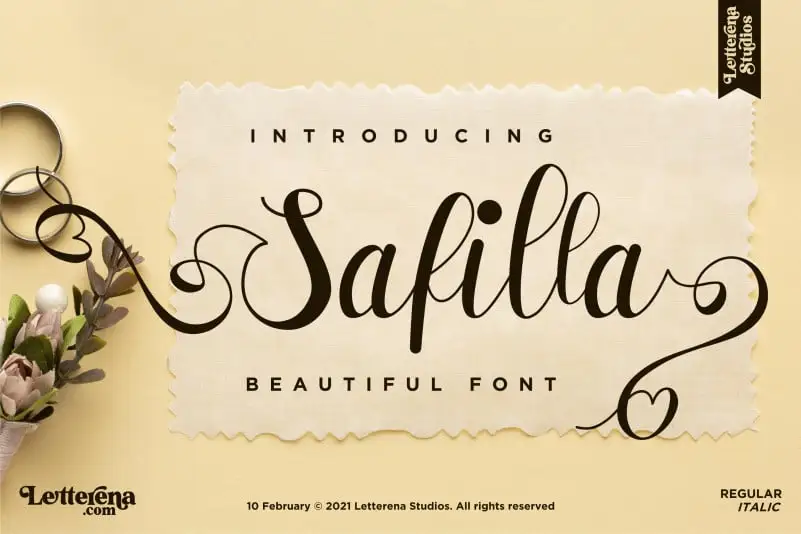
Safilla Calligraphy Font – Download Grátis
Safilla Calligraphy Font é uma elegante fonte de calligrafia romântica criada pela Letterenastudios que traz a essência do design gráfico para sua mais bela expressão. Esta fonte script está projetada com um toque de sofisticação e amor, adequando-se perfeitamente a uma variedade de projetos visuais. Suas linhas finas e delicadas são ideais para criar logos memoráveis, desenvolver projetos de marca, ou até mesmo decorar embalagens de produtos. Além disso, Safilla Calligraphy Font é o complemento perfeito para qualquer projeto que exija um toque único e impecável: desde mugs personalizados a cartões de homenagem, etiquetas para embalagens, nome cards profissionais ou até mesmo fotografias com um touch especial. Com Safilla Calligraphy Font, você pode transformar sua ideia em arte, criando design original e imprimindo uma sensação elegante nos seus projetos. Este é o tipo de font que não só complementa sua estratégia visual, mas também a torna única e memorável. Descubra como Safilla Calligraphy Font pode revolucionar suas próximas criações gráficas!